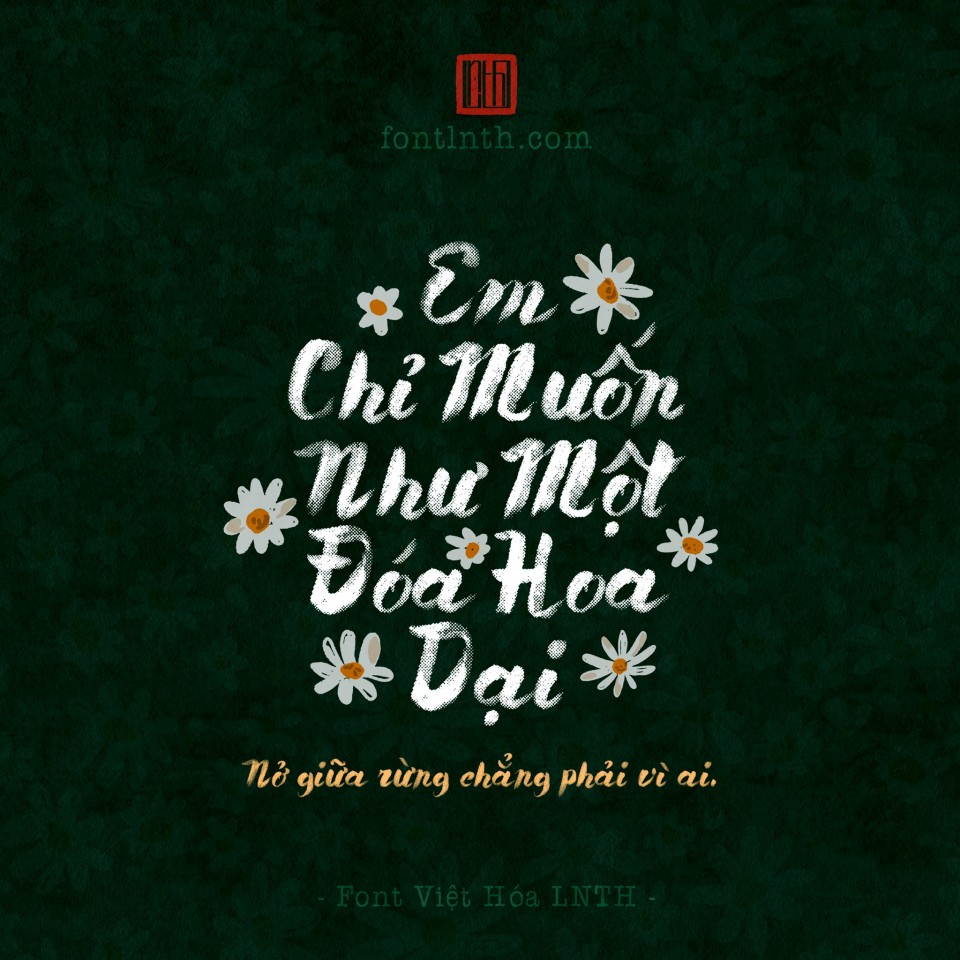
Font việt hóa LNTH Pale Blue Eyes
Trong thế giới thiết kế đồ họa hiện nay, việc lựa chọn một bộ Font Miễn Phí phù hợp là yếu tố then chốt giúp tác phẩm trở nên ấn tượng. Font việt hóa LNTH Pale Blue Eyes nổi lên như một lựa chọn hoàn hảo dành cho những ai yêu thích sự nhẹ nhàng, thanh lịch và đầy cảm xúc. Đây là bộ font script được tinh chỉnh tỉ mỉ, giúp người dùng dễ dàng ứng dụng vào các sản phẩm truyền thông mà không lo lỗi hiển thị tiếng Việt.
Khám phá vẻ đẹp của Font việt hóa LNTH Pale Blue Eyes
Bộ font này mang phong cách viết tay mềm mại, tạo cảm giác gần gũi nhưng không kém phần sang trọng. Với các đường nét bay bổng, Font việt hóa LNTH Pale Blue Eyes cực kỳ phù hợp cho những dự án mang tính nghệ thuật cao như thiệp mời, bìa sách hay các trích dẫn truyền cảm hứng trên mạng xã hội.
Ưu điểm nổi bật trong thiết kế
Điểm mạnh nhất của font chính là khả năng hiển thị mượt mà các ký tự đặc trưng của tiếng Việt. Các dấu câu được đặt ở vị trí cân đối, giúp bố cục chữ trông tự nhiên như viết tay thật. Bên cạnh đó, tính tương thích cao với các phần mềm đồ họa phổ biến giúp các bạn học sinh và nhà thiết kế tiết kiệm tối đa thời gian căn chỉnh.
Cách ứng dụng Font việt hóa LNTH Pale Blue Eyes hiệu quả
Bạn có thể sử dụng font này để làm tiêu đề cho các slide thuyết trình hoặc thiết kế thiệp chúc mừng thầy cô, bạn bè. Sự mềm mại của nó sẽ giúp thông điệp của bạn trở nên chân thành và dễ đi vào lòng người hơn. Lưu ý rằng bạn nên kết hợp với một font không chân đơn giản để tạo sự cân bằng thị giác cho tổng thể bản thiết kế.